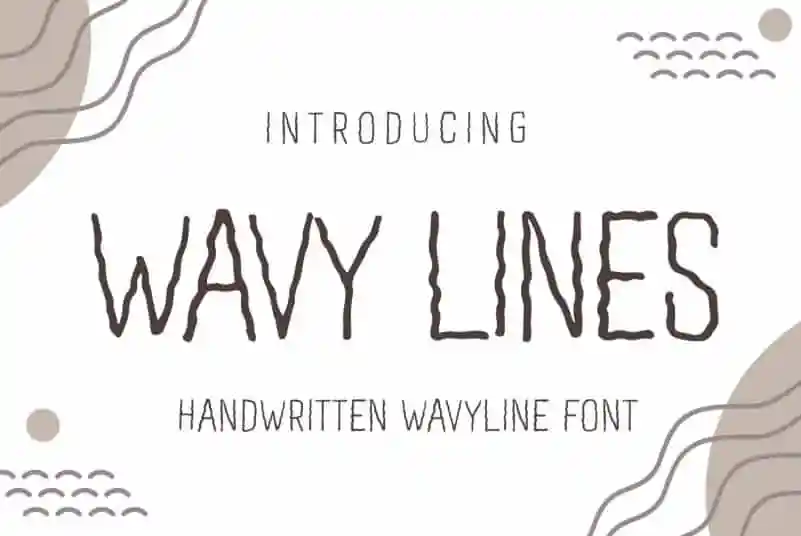
Wavy Lines Display Font – Fonte Grátis
Wavy Lines Display Font
Descobrimos uma nova fonte chamada Wavy Lines Display Font, uma opção perfeita para aqueles que desejam dar um toque único e criativo aos seus projetos visuais. Esta fonte apresenta linhas curvas tanto em maiúsculas quanto em minúsculas, oferecendo uma variedade incrível de possibilidades. A Wavy Lines Display Font é perfeitamente adaptável a diversos tipos de materiais, desde capas de livros até cartazes e postais. Suas linhas onduladas podem ser usadas para adicionar um toque moderno às citações, títulos e embalagens de produtos personalizados. Quem está sempre buscando algo diferente em seus projetos gráficos vai amar a Wavy Lines Display Font. Ela é uma fonte exuberante que ajuda qualquer projeto a ser mais chamativo e encantador, tornando-a a escolha perfeita para os designers criativos. Seja você um profissional de design ou apenas alguém que ama criar belas composições digitais, Wavy Lines Display Font pode tornar suas criações ainda mais vibrantes e memoráveis.